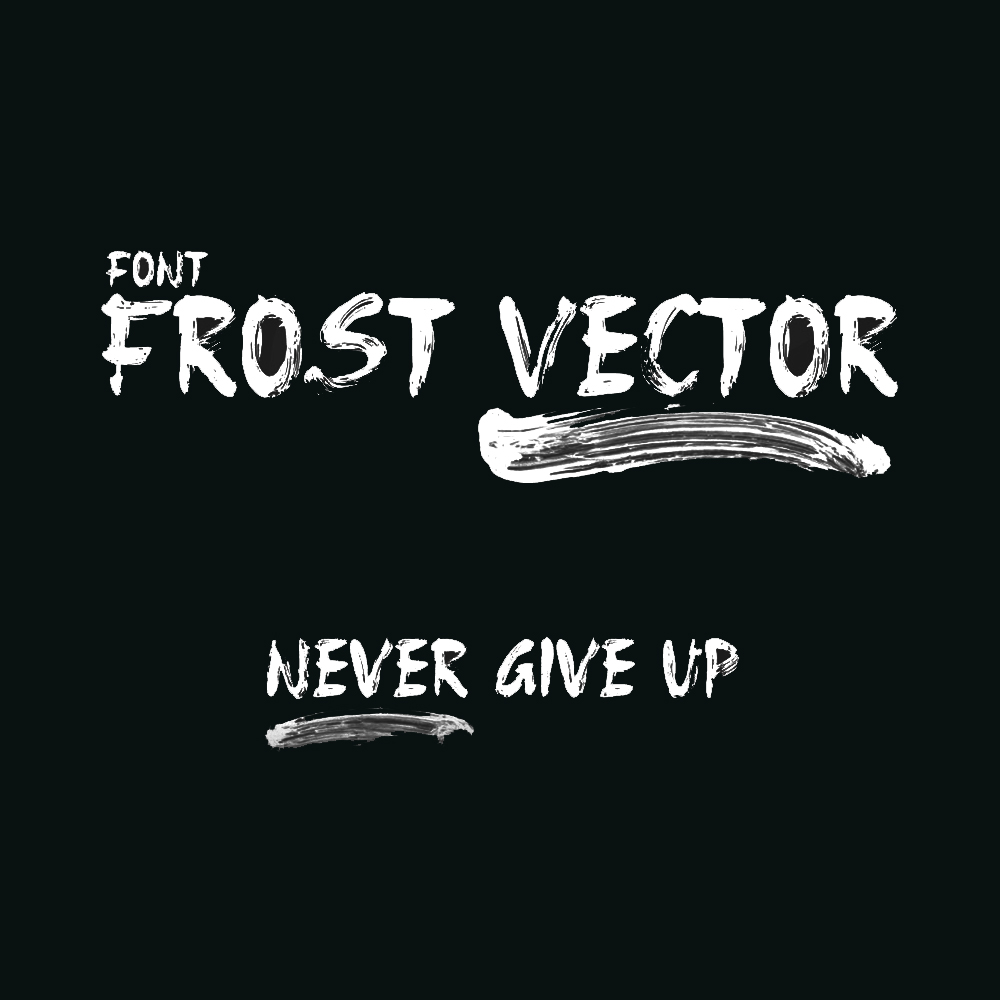
فونت پرمیوم و انگلیسی Frost Vector Font یک فونت نمایشی زیبا است که با سبک قلمموهای زبر ساخته شده است. این فونت با یک قلممو دیجیتال ساخته شده است که دارای کاراکتر زبری است به طوری که یک کاراکتر فونت جسورانه و زیبا ایجاد میکند. میتوان از آن برای پشتیبانی از ظاهر گرافیکی محصول استفاده کرد تا جذابتر و منحصر به فردتر باشد. این فونت برای ساخت پیشنمایشها و جلدها، طراحی لوگو، طراحی هنر خیابانی، طراحی پیراهن و سایر نیازهای گرافیکی مناسب است. همچنین به عنوان هدیه بهترین براش قلممو برای فتوشاپ را برایتان در پک قرار دادهایم تا متن خود را به شاهکار تبدیل کنید.